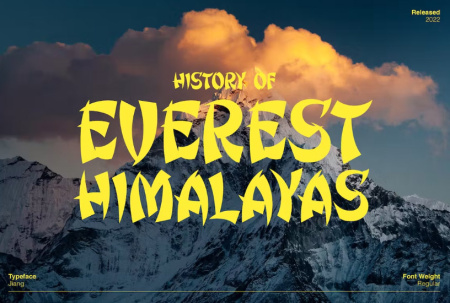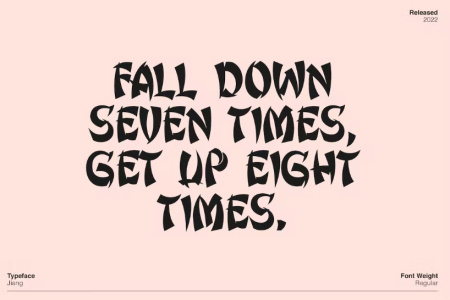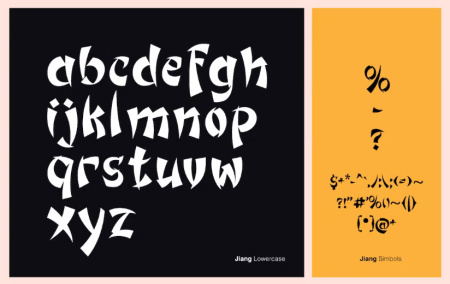
دانلود فونت انگلیسی Jiang
دانلود فونت انگلیسی به سبک آسیایی Jiang
این فونت جذاب و کاربردی برای رستوران ها، فیلم ها، بروشورها، پوسترها، نقل قول ها، یوتیوب، مجلات و لوگوها ایده آل است. ویژگی مهم دیگر این است که این فونت چند زبانه است. شروع به استفاده از جیانگ در پروژه های خود کنید تا آنها را برجسته کنید. برای دانلود فونت انگلیسی Jiang از جی اف ایکس دانلود به ادامه مطلب مراجعه کنید.